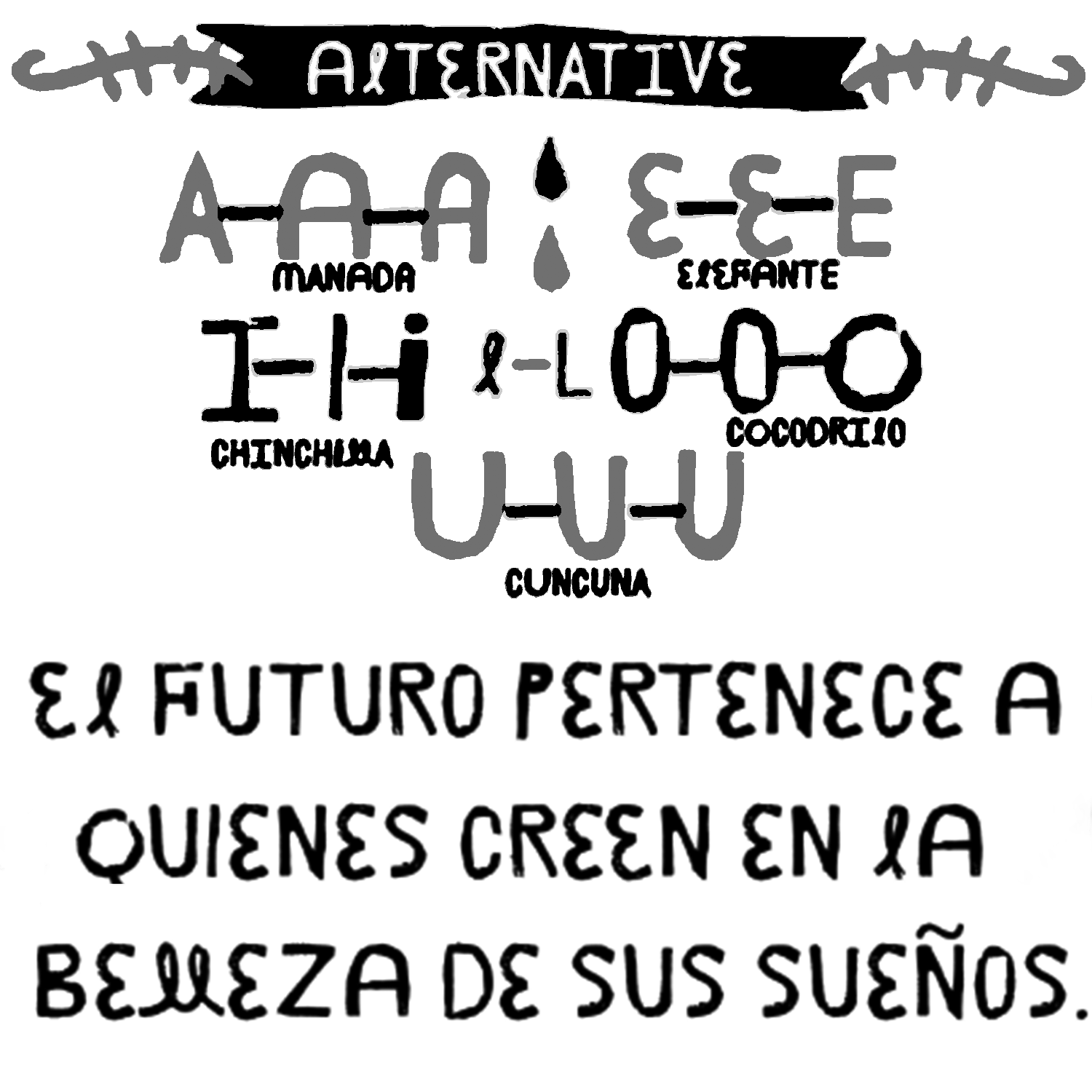
Janmeid
| Descripción | Janmeid es una tipografía totalmente hecha a mano, con todos sus acentos y caracteres cirílico y griego, cuenta con alternativas y ligaduras variadas, además contiene 3 dingbat set, el primero es Xtreme, el segundo es tales y el tercero Line, ayudan a que las letras parezcan Swash algo mucho más decorativo, la idea es hacer una tipografía dulce, loca y divertida, inquieta |
| Familia(s) | Janmeid Regular, Janmeid Xtreme, Cuentos de Janmeid, Línea Janmeid. |
| Estilos | 4 |